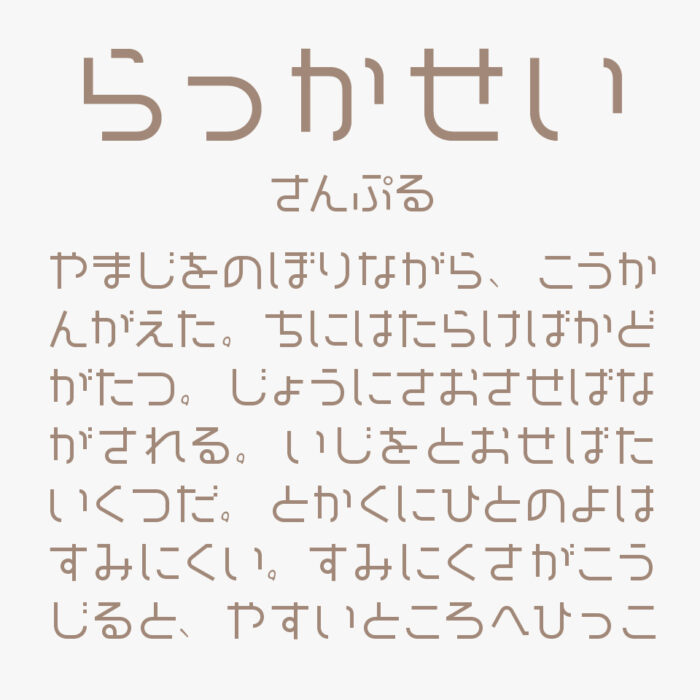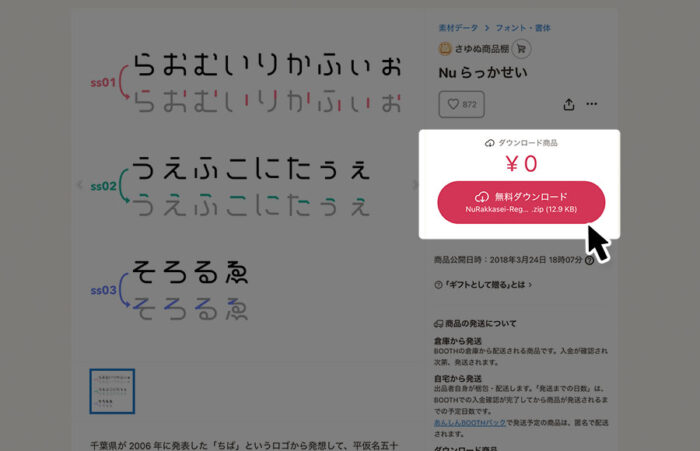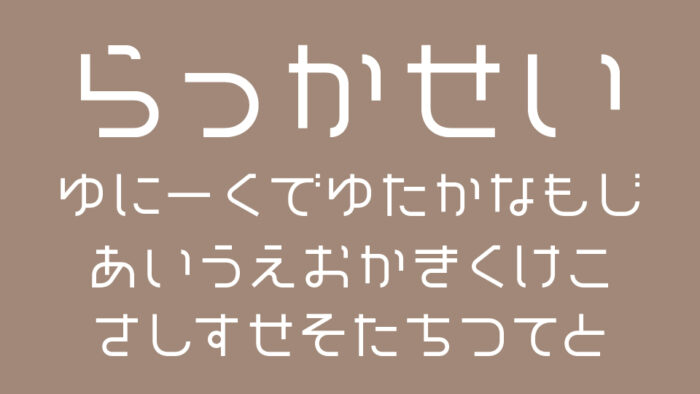
Nu らっかせいフォントは、千葉県が発表した「ちば」ロゴからヒントを得て制作された丸みが可愛いデザインフォントです。
幾何学的でモダンにも見えますが、やわらかな丸みと均一な線幅が脱力感もある親しみやすいフォントとなっています。
ひらがなのみの収録フォントですが、読みやすさとかわいらしさのあるフォントなので、ロゴなどにぴったりです。